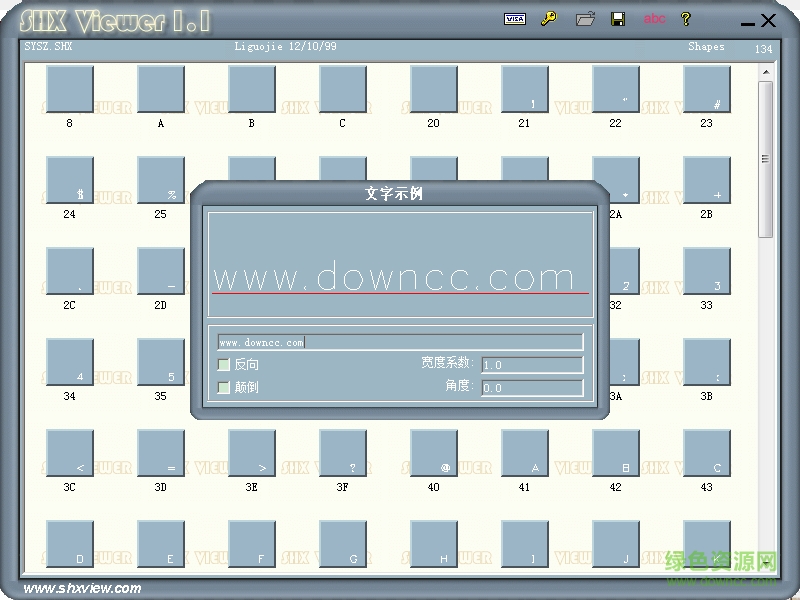
在CAD中畫鋼筋圖時(shí),先建立新的文字樣式—鋼筋樣式,就要用到鋼筋符號(hào)字體:大字體SYSZ.SHX。小字體為SYFZ.SHX。這是一種CAD的新字型能讓CAD自帶的小字型文件完美配合。該字型適當(dāng)?shù)陌炎指咦髁苏{(diào)整,加高了一點(diǎn),使?jié)h字和數(shù)字、字母的高度比較協(xié)調(diào)(漢字自高略高于字母和數(shù)字)。使用了它,您現(xiàn)在可以放心的用各種瀏覽圖的軟件來(lái)瀏覽您的圖之中的漢字了!